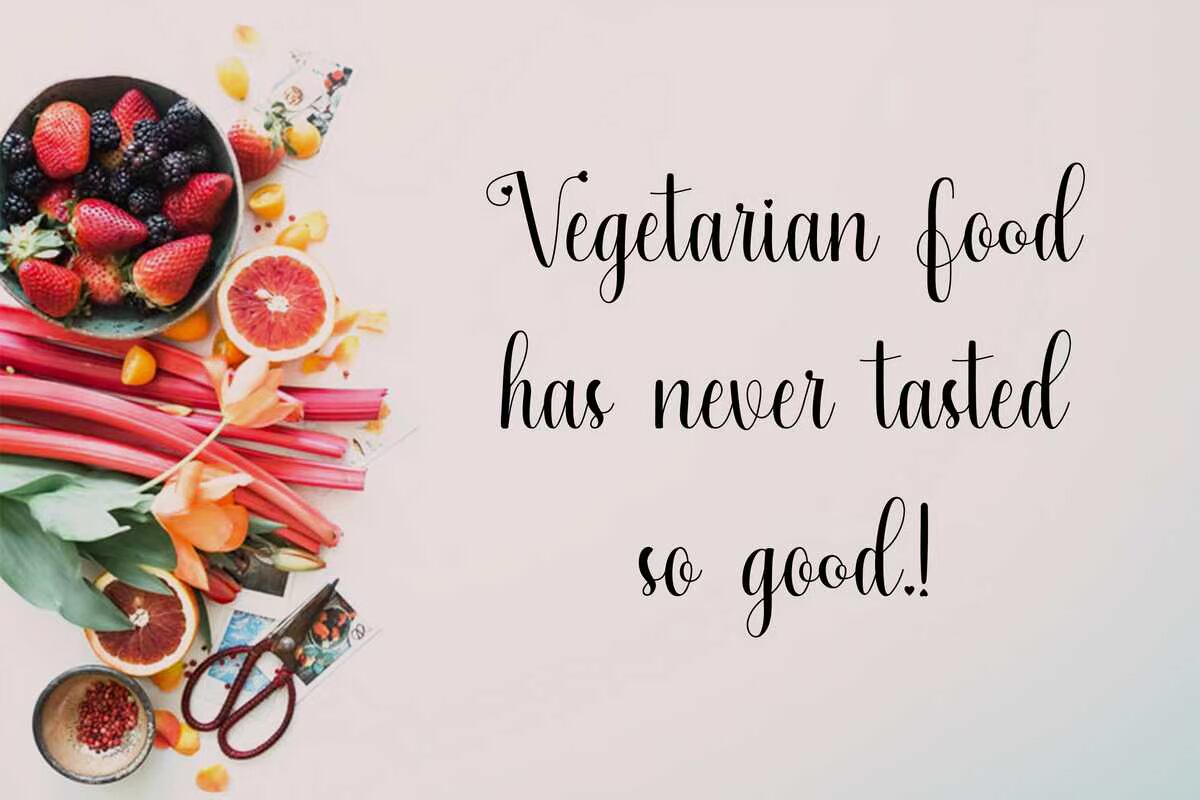
HANIFAHISAGREATSCRIPTONT.Wrapped位于带有运行装饰的子笔画中。此字体可以根据需要进行更改,无论其字体是普通字体、弹跳字体、休闲字体还是无尾字体。因为它是此字体的首选替代字体。适用于婚礼庆典、报价、标签、徽标、社交媒体、生日、情人节等特殊场合,圣诞节和你需要的任何东西。Hani His AgreatScriptFont。用一种不带装饰的方式包装在桌面下。无论是普通、弹跳、休闲还是无尾,此字体都可以根据需要进行更改。因为此字体是可选的。适用于婚礼庆典、报价、标签、徽标、社交媒体、特别节日生日、情人节、,圣诞节和任何你需要的东西。